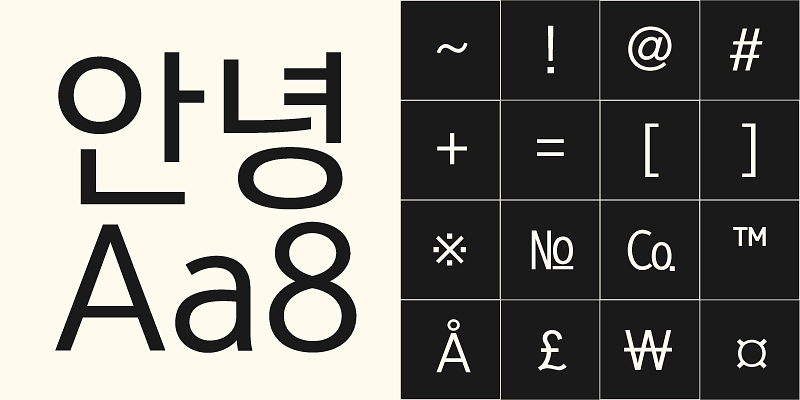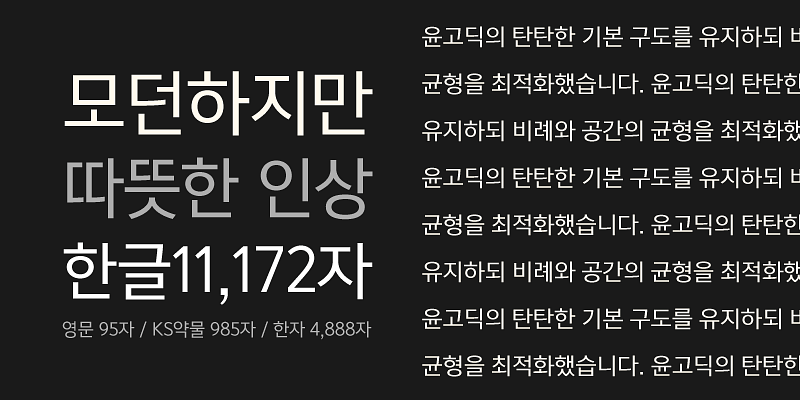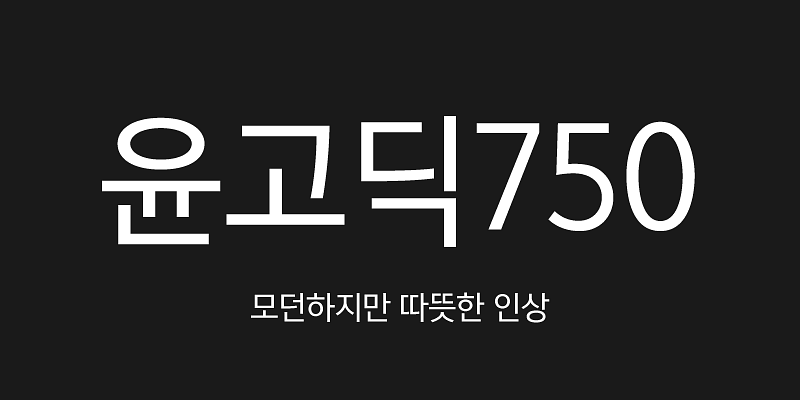
「Yoon Gothic 700」ファミリーは、多様なテキストコンテンツの本文とタイトルの両方に柔軟に対応します。710 から 790 まで 9 つの細かく調整された太さで構成されており、750 が最もよく使われます。「Yoon Gothic 700」は、「Yoon Gothic」シリーズの堅牢な基本構造を継承しながら、プロポーションとスペースのバランスが微調整されています。印象的な内部スペースのレイアウトにより、優れた可読性が実現されています。それぞれの太さに合わせて緻密にデザインされた英字、数字、ユニークな特殊文字は、モダニティの最高峰といえます。このフォントは、韓国語と英語の両方を使用するデザインでシームレスに調和するように綿密に構築されています。